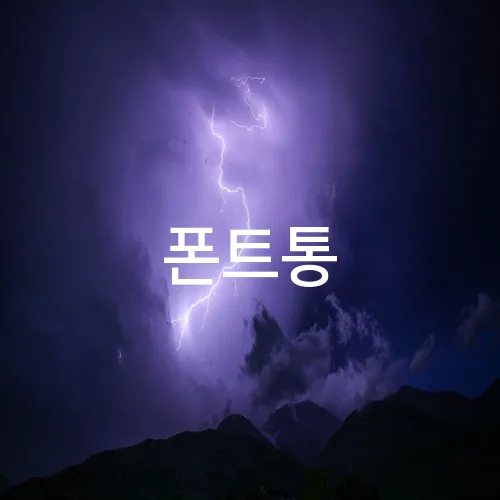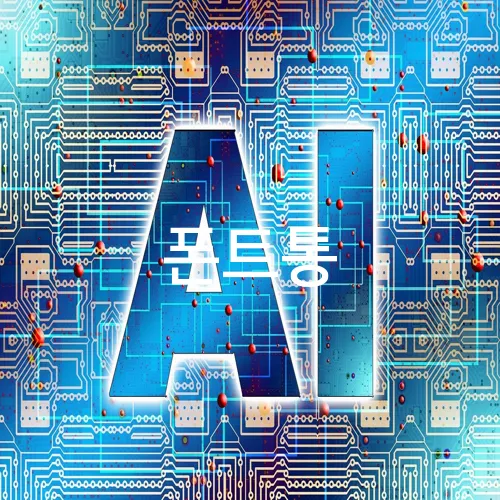
폰트통: 10가지 필수 무료 폰트 추천!
1. 폰트통에서 엄선한 최고의 무료 폰트
최고의 무료 폰트를 제공하는 폰트통
폰트통은 수많은 디자이너와 콘텐츠 제작자들에게 인기를 끌고 있는 폰트 플랫폼입니다. 이곳에서는 다양한 스타일과 용도의 무료 폰트를 제공합니다. 특히 국내외의 유명 디자이너들이 참여하여 배포하는 고품질의 폰트가 많아 더욱 신뢰할 수 있습니다.
대표적인 무료 폰트로는 ‘나눔고딕’, ‘배달의민족 주아체’, ‘본고딕’ 등이 있습니다. 각각의 폰트는 그들의 고유한 특성을 가지고 있으며, 다양한 상황에서 활용하기에 적합합니다. 이처럼 폰트통은 디자인 작업 시 스타일과 가독성을 모두 고려한 폰트 선택이 가능합니다.
각 분야에 맞춘 폰트 추천
디지털 콘텐츠를 제작할 때는 폰트 선택이 중요합니다. ‘나눔바른고딕’은 깔끔한 인상을 주어 웹페이지, 모바일 앱 등에 자주 사용됩니다.
출판물이나 프레젠테이션 디자인에는 ‘한컴 말랑말랑체’가 좋습니다. 귀여운 인상을 주며 시선을 사로잡을 수 있습니다.
감성적인 디자인을 원하신다면 ‘김남윤체’를 고려해보세요. 독창적이고 예술적인 느낌을 주어 특별한 프로젝트에 이상적입니다.
폰트통에서의 적용 사례
폰트통을 통해 제공되는 무료 폰트를 활용하여 다양한 프로젝트에 적용할 수 있습니다. 예를 들어 학교 교육 자료나 기업 브로슈어 제작 시 보다 전문적이고 스타일리시한 결과물을 얻을 수 있습니다.
또한 개인 블로그나 유튜브 채널의 썸네일 제작에서도 그 효과를 입증할 수 있습니다. 무료 폰트지만, 다양한 환경에 맞춰 적용할 수 있는 유연함이 큰 장점입니다.
폰트통을 이용해 정리된 목록을 활용하면 빠르게 원하는 스타일의 폰트를 선택할 수 있습니다. 공식 사이트를 통해 최신 폰트와 업데이트 정보를 확인하시길 추천합니다.
2. 디자이너들이 사랑하는 인기 폰트
인기 폰트 1: 노토 산스(Noto Sans)
노토 산스(Noto Sans)는 구글에서 제공하는 무료 폰트로, 다양한 언어와 문자를 지원하는 것이 특징입니다. 이 폰트는 깔끔하고 현대적인 디자인으로 인해 많은 디자이너들에게 사랑받고 있습니다. 특히 한글, 영어, 중국어 등 여러 언어에 최적화되어 있어 다국어 프로젝트에 최적입니다.
노토 산스는 가독성이 뛰어나 웹사이트, 앱 디자인, 인쇄물 등 다양한 분야에 적용할 수 있습니다. 이 때문에 글로벌 기업에서도 자주 사용되며, 사용자 경험을 최적화하는 데 큰 도움을 줍니다.
– 다국어 지원: 한국어, 일본어, 중국어, 아랍어 등
– 다양한 굵기와 스타일 제공
인기 폰트 2: 나눔고딕(Nanum Gothic)
나눔고딕은 국내 포털 사이트 네이버가 개발한 무료 폰트로, 깔끔하고 세련된 디자인이 특징입니다. 이 폰트는 현재까지도 꾸준히 사랑받고 있으며, 웹과 모바일 환경 모두에 최적화되어 있습니다.
나눔고딕은 특히 한글에서 뛰어난 가독성을 자랑하며, 블로그나 웹사이트에서 자주 사용됩니다. 이 폰트는 기본 폰트로 설정해도 손색이 없는 완성도를 지니고 있습니다.
– 네이버에서 제공하여 한글 문서에 특화
– 다양한 스타일: 고딕, 바른고딕, 스퀘어 등
– 사용자 친화적이며 다양한 디자인 활용 가능
인기 폰트 3: 오픈 산스(Open Sans)
오픈 산스(Open Sans)는 글로벌 폰트 제작사인 어도비(Adobe)가 디자인한 무료 폰트로, 최근 들어 특히 웹 개발자 사이에서 인기가 높습니다. 이 폰트는 읽기 쉬운 디자인과 함께 다양한 굵기 옵션을 제공하여 디지털 콘텐츠에 자주 사용됩니다.
오픈 산스는 전 세계 여러 웹사이트에서 기본 글꼴로 채택되었으며, 간단하면서도 현대적인 느낌을 줍니다. 이 폰트는 프로젝트의 완성도를 높이는 데 기여하며, 브랜드 이미지 향상에도 도움을 줄 수 있습니다.
– 웹 및 인쇄 매체에 모두 적합
– 다양한 굵기: Light, Regular, Semi-Bold 등
이 세 가지 폰트는 국내외 디자이너들 사이에서 널리 사용되며, 다양한 디자인 프로젝트에 활용 가능합니다. 유용하고 실용적인 무료 폰트를 찾고 계시다면 위의 폰트들을 고려해보시기 바랍니다.
3. 상업용으로도 활용 가능한 무료 폰트
상업용으로도 활용 가능한 무료 폰트 추천
디자인 작업을 하다 보면 무료로 이용할 수 있으면서도 상업용으로 사용 가능한 폰트를 찾는 일이 생각보다 쉽지 않습니다. 많은 폰트는 개인 용도에 한해 무료로 제공되지만, 상업적 사용에는 별도의 라이선스가 필요한 경우가 많기 때문입니다. 이 글에서는 상업적 프로젝트에 부담 없이 활용할 수 있는 무료 폰트를 소개합니다.
– 나눔고딕(NanumGothic): 네이버에서 제공하는 나눔고딕은 깔끔하고 현대적인 디자인으로 웹사이트, 프린트 등 다양한 용도에 적합한 폰트입니다. 특히 한글 표현에 강점이 있어 한국어 콘텐츠에 많이 사용됩니다.
– IBM Plex Sans: IBM Plex Sans는 글로벌 디자인 환경에서 각광받는 폰트입니다. 깔끔한 고딕 스타일로 웹과 앱에서 쉽게 사용될 수 있습니다. 오픈 소스 폰트로 상업적 사용도 자유롭습니다.
– 카페24 써라운드(Cafe24 Ssurround): 카페24에서 제공하는 이 폰트는 부드럽고 친근한 느낌을 주는 서체로, 특히 유아용 및 교육 관련 콘텐츠에 잘 어울립니다. 카페24 공식 사이트에서 무료로 다운받을 수 있으며, 다양한 경로를 통해 공유 가능합니다.
좀 더 특별한 무료 폰트
또한, 특별한 느낌을 내고 싶을 때 사용할 수 있는 무료 폰트들도 존재합니다.
– 배달의민족 한나체 Pro: 특유의 귀여운 필체가 잘 드러나는 폰트입니다. 배달의민족에서 제공하는 이 글꼴은 포스터, SNS 콘텐츠 등에서 주목을 끌기 좋은 스타일입니다.
– 롯데마트Dream: 롯데마트에서 배포하는 이 폰트는 현대적이고 깔끔한 디자인이 특징입니다. 다양한 프로모션 디자인에 적합하며 상업용으로 자유롭게 사용 가능합니다.
4. 한글과 영문 모두 지원되는 다국어 폰트
다국어 폰트의 중요성
한글과 영문을 동시에 지원하는 다국어 폰트는 글로벌 비즈니스 환경에서 필수적입니다. 이러한 폰트를 사용하면 다양한 언어의 사용자에게 일관된 브랜드 이미지를 제공할 수 있습니다. 예를 들어, 구글의 ‘나눔바른고딕’은 한글과 영문의 조화로운 조합으로 인기를 얻고 있습니다.
추천 다국어 폰트 목록
– 나눔 바른펜: 클래스 있는 손글씨 느낌을 주는 폰트로, 가독성이 뛰어납니다. 문서 작업이나 프레젠테이션에 적합합니다.
– 본고딕(Noto Sans): 구글과 어도비가 공동 개발한 폰트로, 세계 여러 언어를 지원합니다. 다양성을 중시하는 기업에게 이상적입니다.
– 맑은 고딕: 마이크로소프트의 기본 폰트로, 깔끔하고 명료한 디자인을 자랑하며, 일반 문서부터 오피스 작업까지 널리 사용됩니다.
– 플라이타입: 폰트릭스의 다국어 지원 폰트로, 인쇄물이나 디지털 콘텐츠에 모두 적합합니다. 다양한 굵기 옵션이 있어 선택의 폭이 넓습니다.
다국어 폰트 선택 시 고려사항
다국어 폰트를 선택할 때는 가독성, 지원 범위, 스타일을 고려해야 합니다. 가독성은 사용 목적에 따라 중요도가 달라지며, 지원 범위는 사용자의 국적과 언어를 고려한 결정적 요인입니다.
스타일은 브랜드 이미지와 일치해야 하며, 제공되는 굵기나 스타일 다양성도 활용성에 큰 영향을 미칩니다. 이러한 요소를 고려하면 완성도 높은 디자인 작업을 할 수 있습니다.
5. 폰트통 추천: 타이포그래피의 매력 발산
타이포그래피의 매력 발산: 폰트통 추천 무료 폰트
타이포그래피는 문서나 디자인에서 중요한 요소입니다. 폰트 선택은 디자인의 분위기와 전달하고자 하는 메시지를 크게 좌우하죠. 특히 무료로 사용할 수 있는 폰트를 찾는 것은 까다로울 수 있는데, 그렇기 때문에 폰트통에서는 효율적이고 매력적인 폰트를 추천해드립니다.
먼저, ‘나눔스퀘어’ 폰트는 현대적이고 깔끔한 인상을 줍니다. 이는 기업 사이트나 공식 문서에서 많이 사용되며, 한글의 아름다움을 잘 살려 다양한 프로젝트에 적합합니다.
‘에스코어 드림’은 네이버에서 제공하는 무료 폰트로, 가독성이 높고 스타일이 현대적입니다. 크고 작은 사이즈에서도 균형 잡힌 레이아웃을 유지합니다.
‘본고딕’ 폰트는 Adobe와 구글의 협력으로 제작된 글로벌 폰트입니다. 다국어 지원이 뛰어나며, 다양한 플랫폼에서 일관된 타이포그래피를 제공합니다.
– 나눔고딕: 고딕체 중에서는 가장 인기가 많습니다. 다양한 굵기로 제공되어 디자인의 유연성을 높여줍니다.
맞춤형 디자인에는 여러 폰트를 조합하는 것이 좋습니다. 제목과 본문에 각각 다른 폰트를 적용하면 시각적 차이를 만들어 내어 디자인의 완성도를 높일 수 있습니다.
– 제목: 강한 인상을 주기 위해 굵고 독특한 서체를 선택
– 본문: 가독성을 고려한 깔끔한 서체 활용
무료 폰트의 한계 및 대처법
물론 모든 폰트가 본인의 프로젝트에 100% 적합한 것은 아닙니다. 때로는 필요한 스타일이나 문자 지원이 부족할 수 있습니다. 이럴 때는 어떤 상황에서도 기본적인 가독성을 제공하는 폰트를 우선적으로 선택하는 것이 중요합니다.
또한, 포토샵이나 일러스트레이터 같은 디자인 프로그램에서 폰트를 미리 적용해 보고 여러 가지 방식으로 조정해보는 것이 좋습니다. 이렇게 하면 실제 활용 시 생길 수 있는 문제를 사전에 방지할 수 있습니다.
무료 폰트는 디자인의 출발점이 될 수 있습니다. 잘 활용한다면, 독창적이고 완성도 높은 결과물을 얻을 수 있을 것입니다. 공식 사이트에서 정확한 라이선스 정보를 확인하고, 프로젝트에 맞춘 서체 선택으로 매력적인 디자인을 완성하세요.